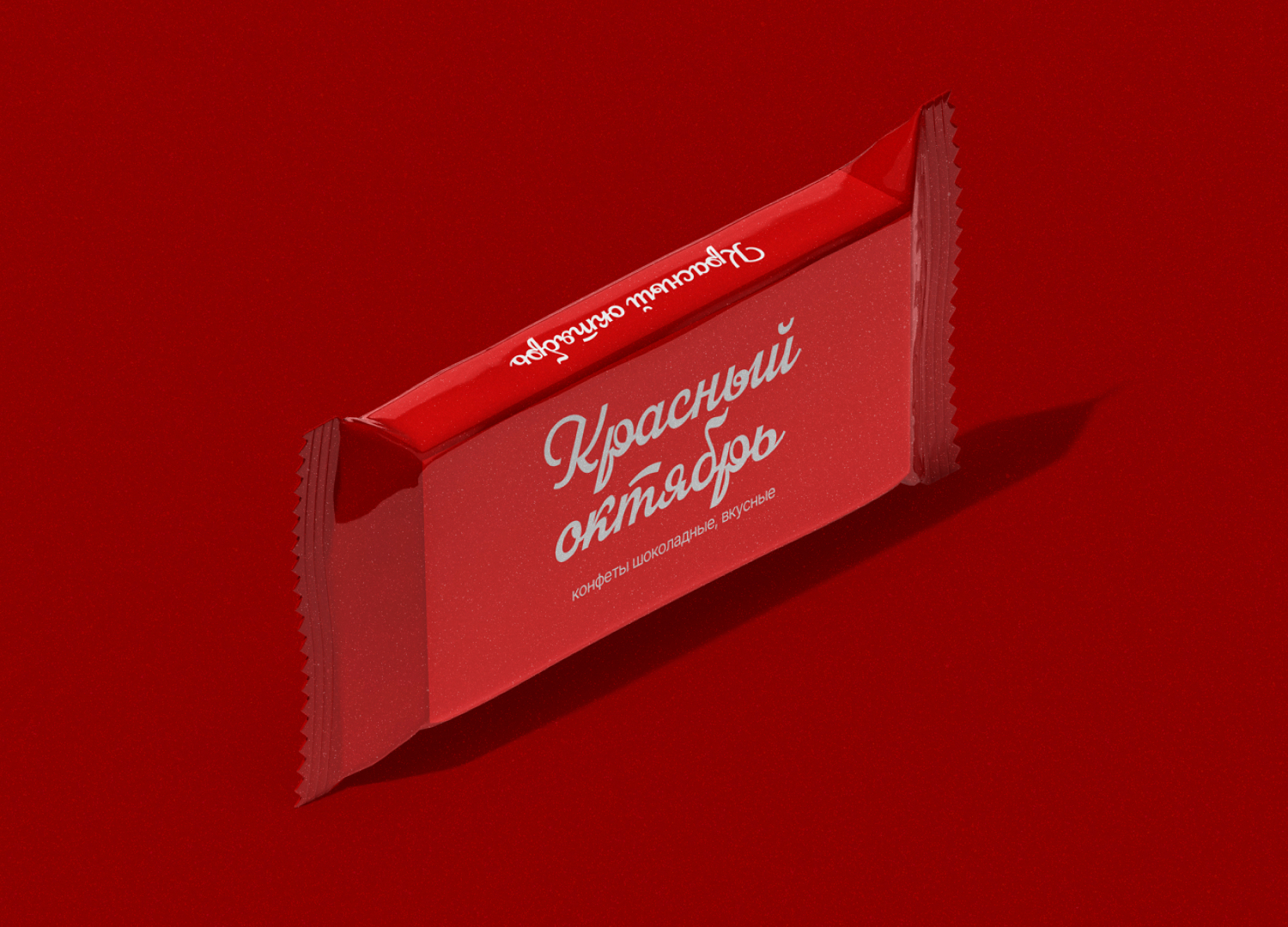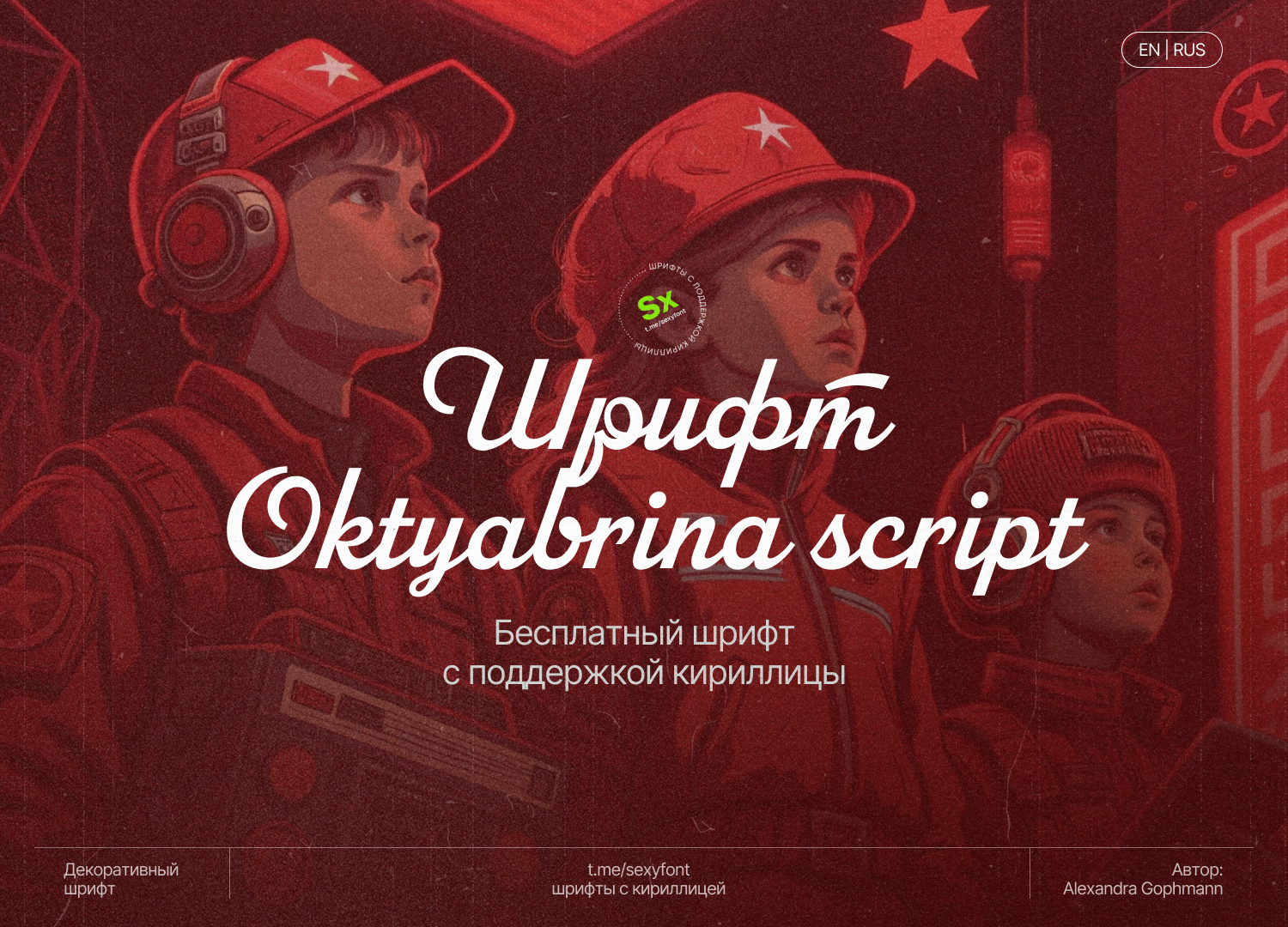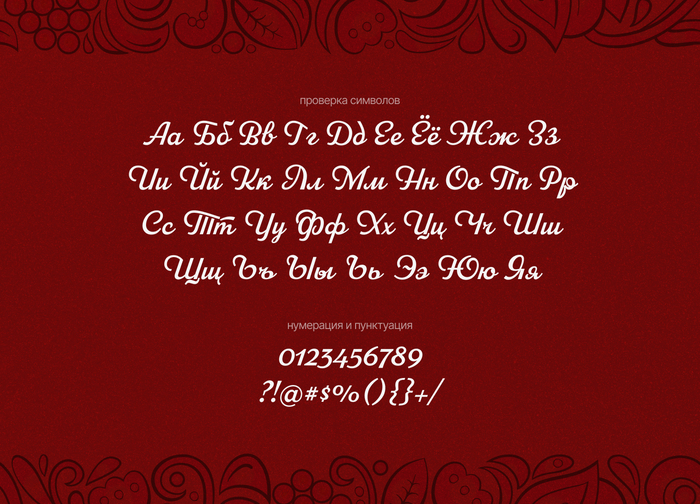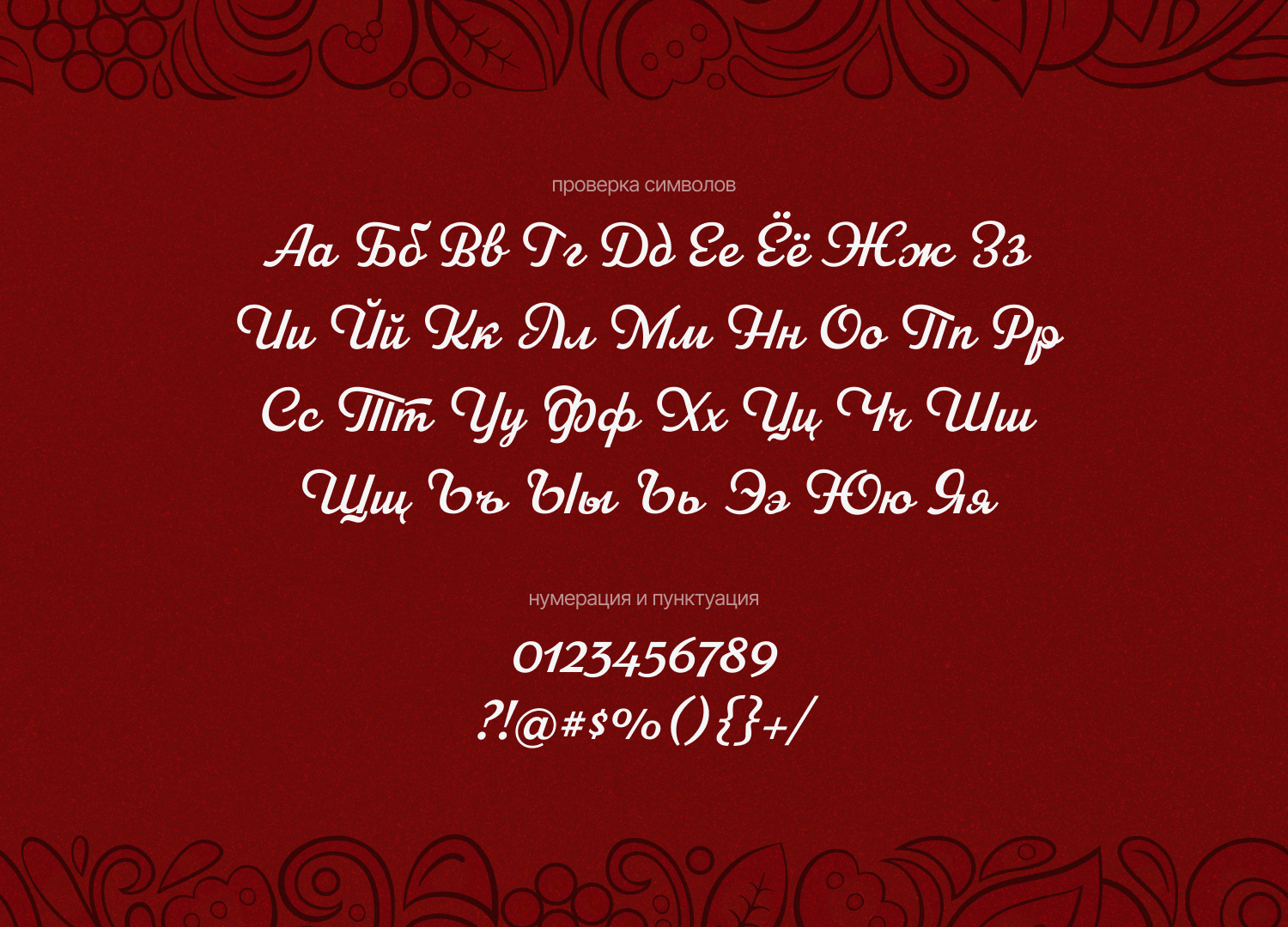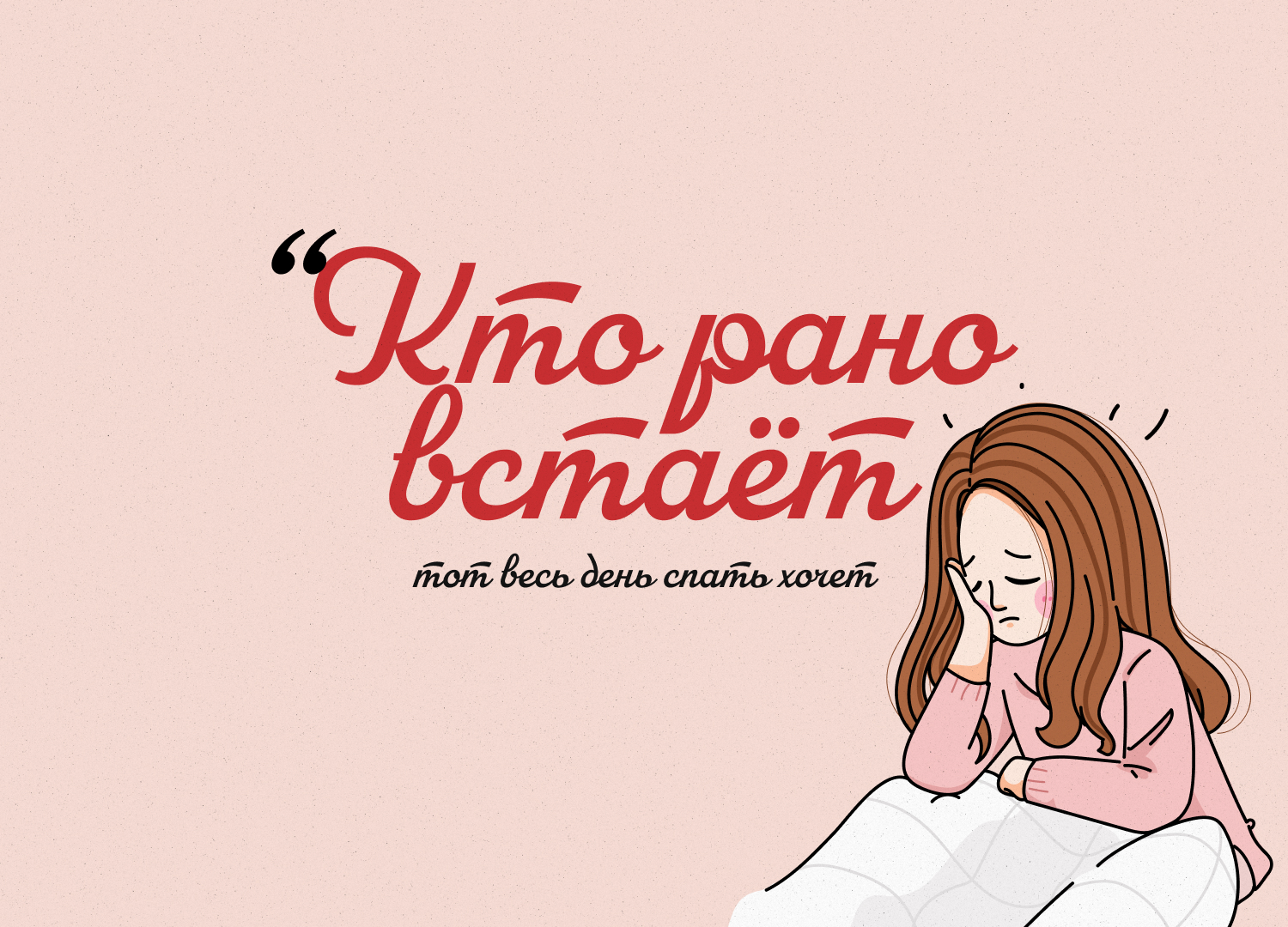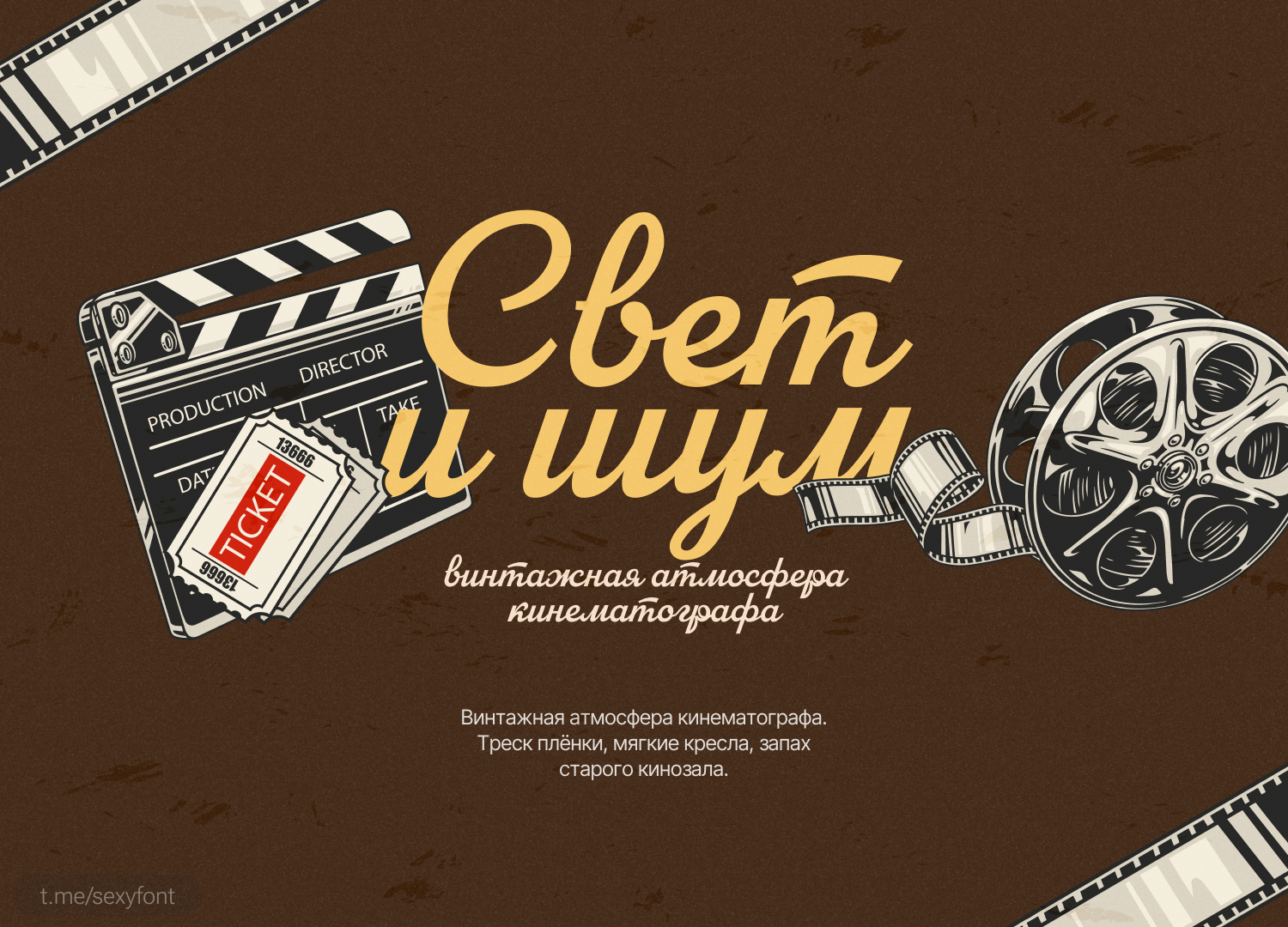
Шрифт Oktyabrina Script
Новая презентация! Oktyabrina Script — декоративный рукописный шрифт, созданный дизайнером Александрой Гофманн. Шрифт, который не просто пишет, а заявляет! Немного пионерский характер)